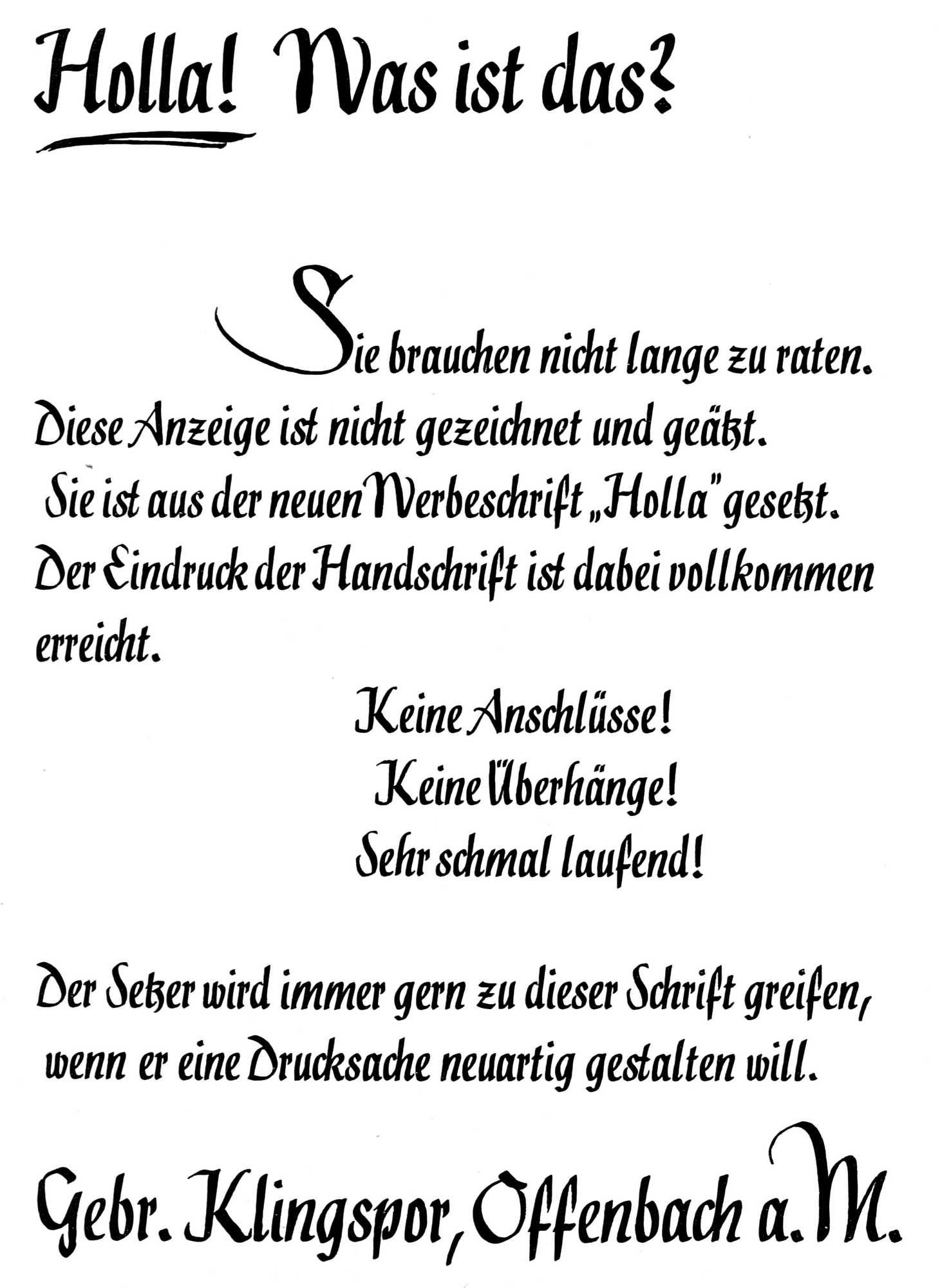
Font-Wiki: Holla
• 1932
• Antiqua Schreibschrift
Die Holla ist eine schmallaufende, unverbundene Schreibschrift von Rudolf Koch. Sie erschien 1932 bei Klingspor in Offenbach von 12 bis 60 Punkt in Blei sowie als Holzbuchstabenschrift. Zusätzlich erhältlich waren Schwungbuchstaben und Unterstreichungen, um den handgeschriebenen Charakter zu unterstützen.
Eine kostenlose Digitalisierung (ohne Schwungbuchstaben) gibt es von Dieter Steffmann.